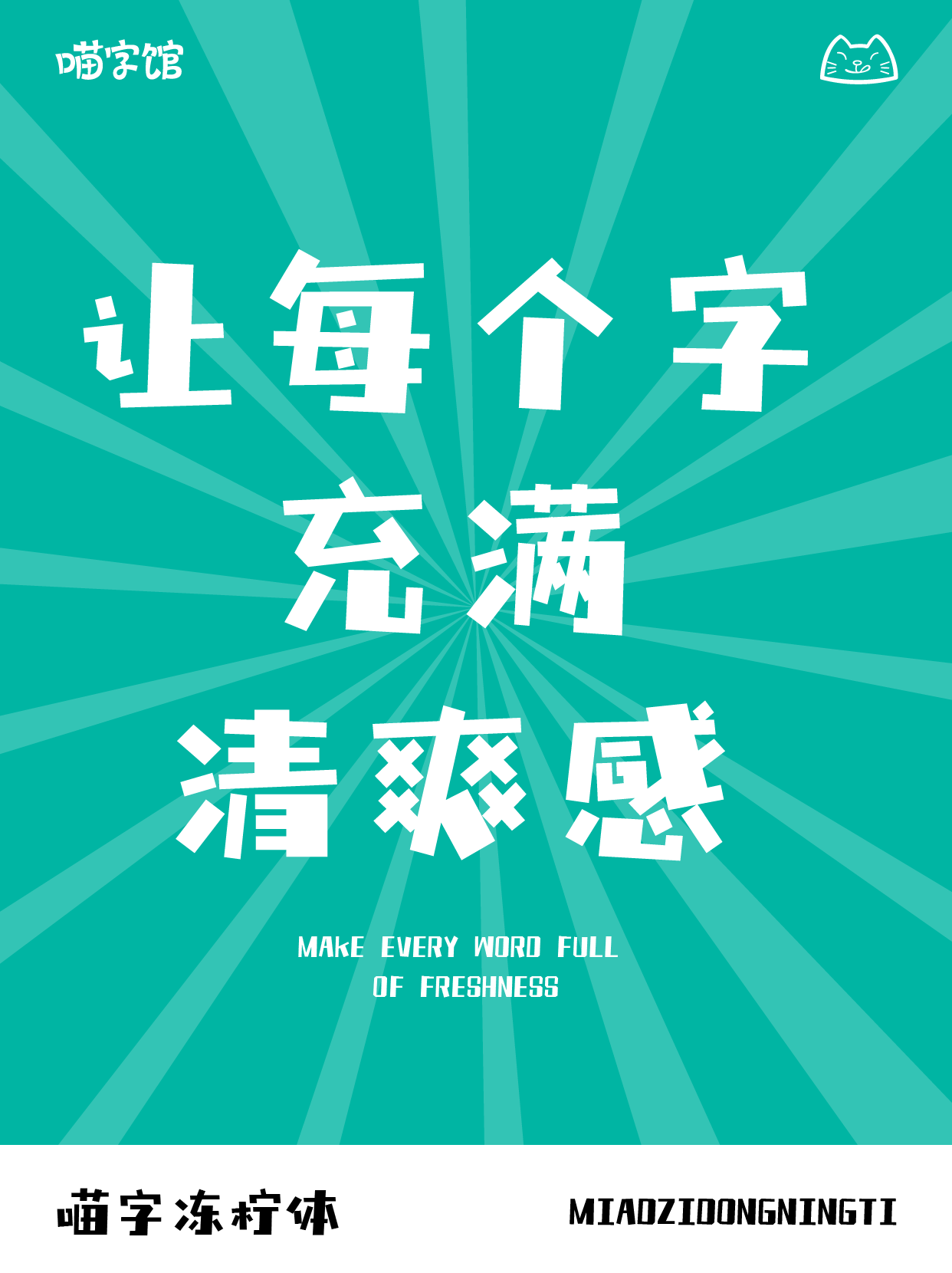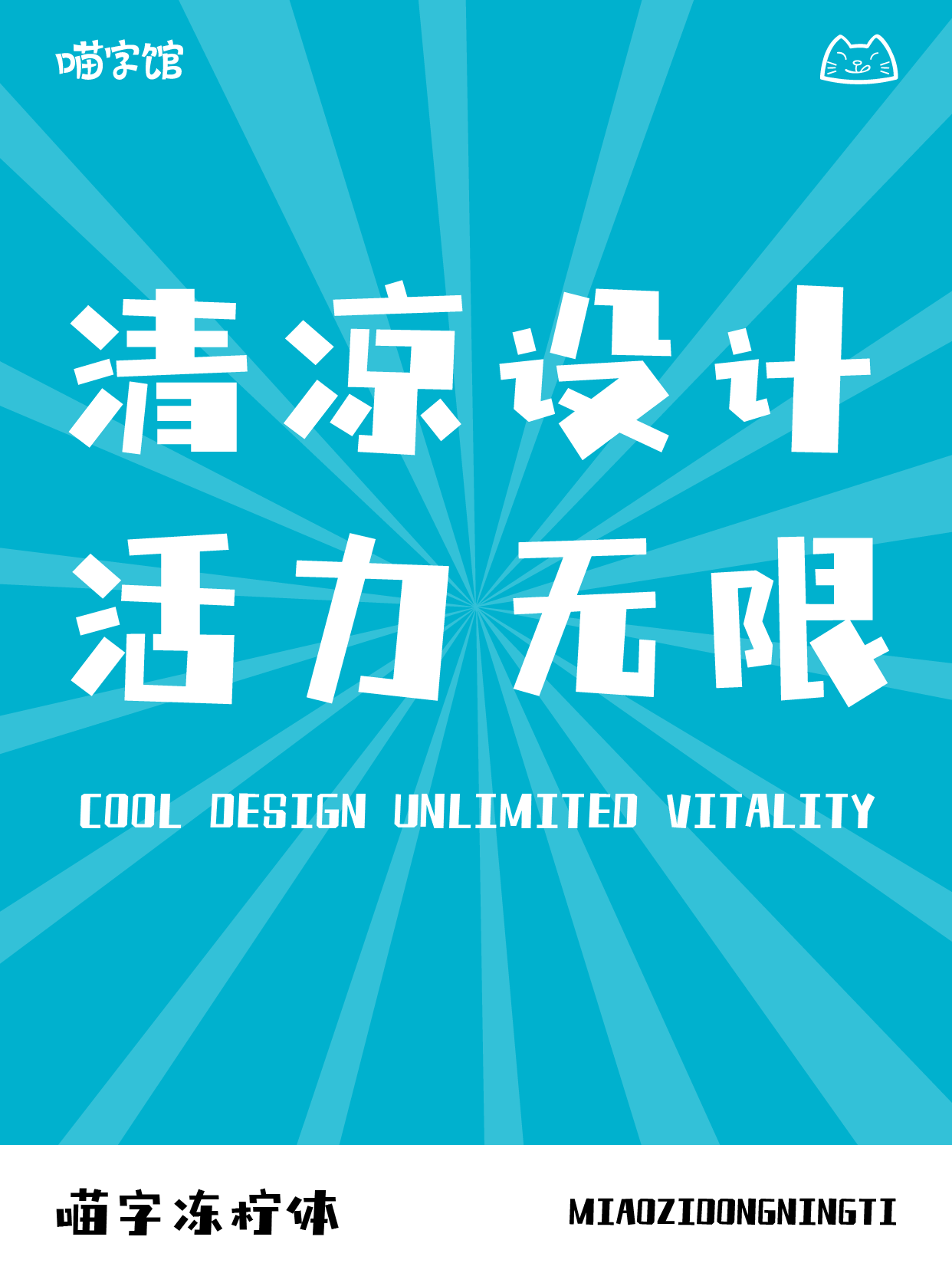
喵字冻柠体
MiaoZiDongNingTi
喵字冻柠体,是一款专为海报设计领域所量身打造的定制级细分字库。其设计灵感源自清爽夏日里的一抹柠檬黄,将现代简约与时尚元素巧妙融合,旨在为海报带来耳目一新的视觉体验。冻柠体的字形结构均衡而富有张力,笔画间微妙的粗细变化模拟了冰块碰撞的动态美感,赋予了文字独特的视觉冲击力。